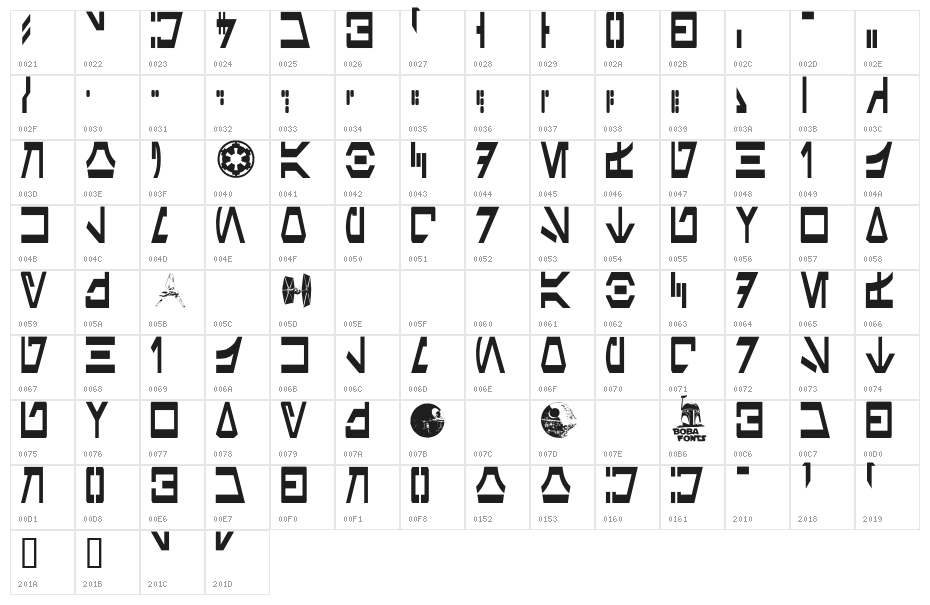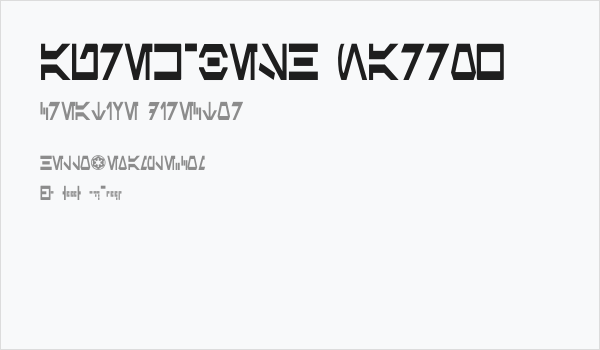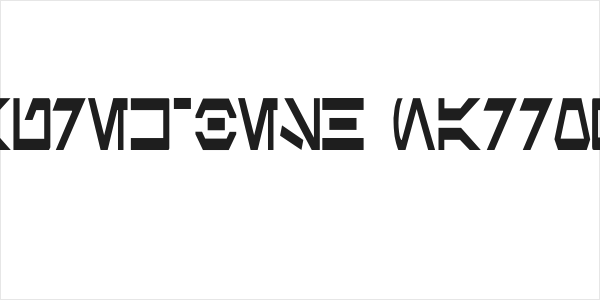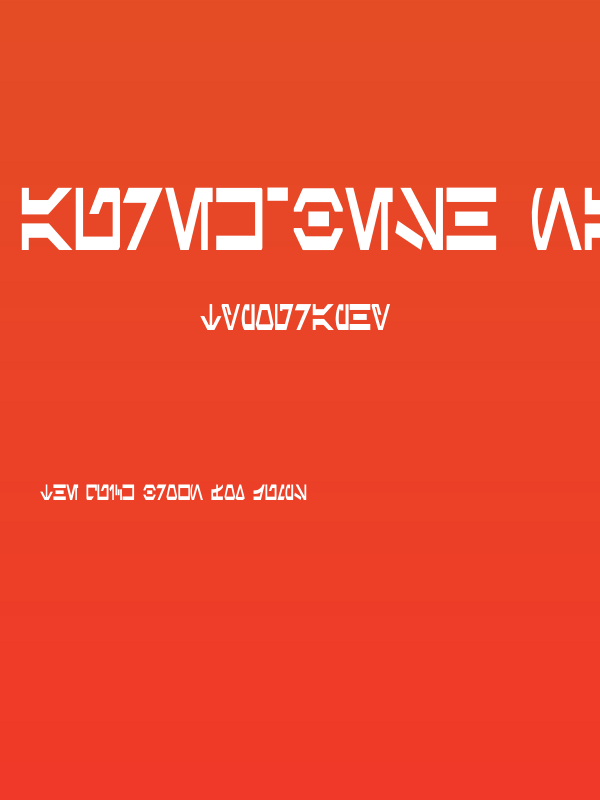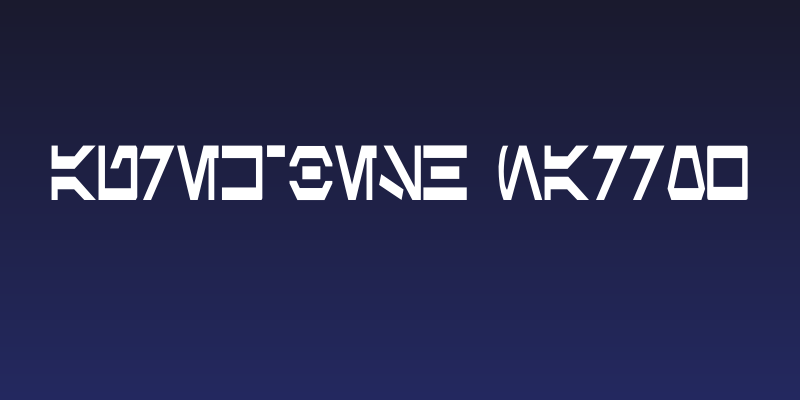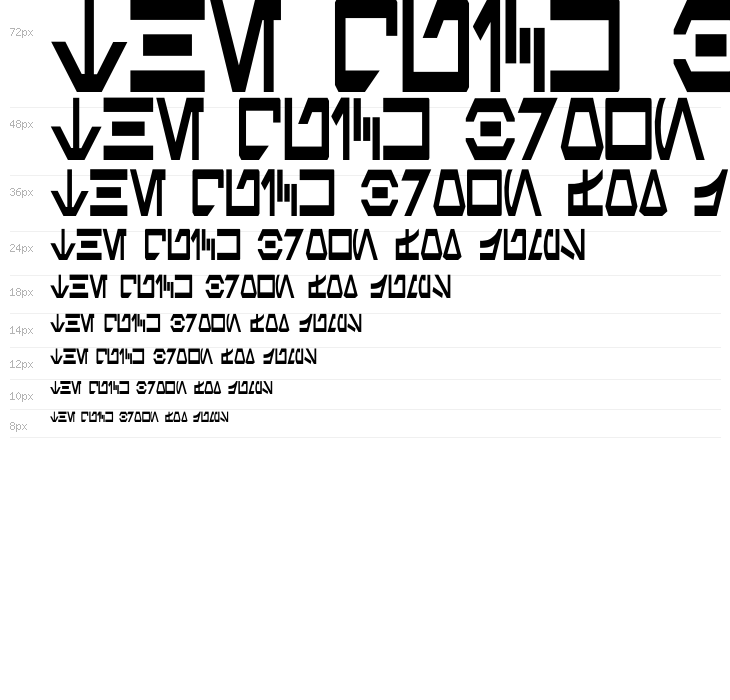
Aurek-Besh Narrow Font
| Gesamtstil | Futuristic |
| Anwendungsfall | Logos, Headlines, Themed Events |
| Vorgeschlagene Projekte | Ideal for sci-fi themed designs, video game interfaces, movie posters, and any project needing a futuristic or extraterrestrial touch. |